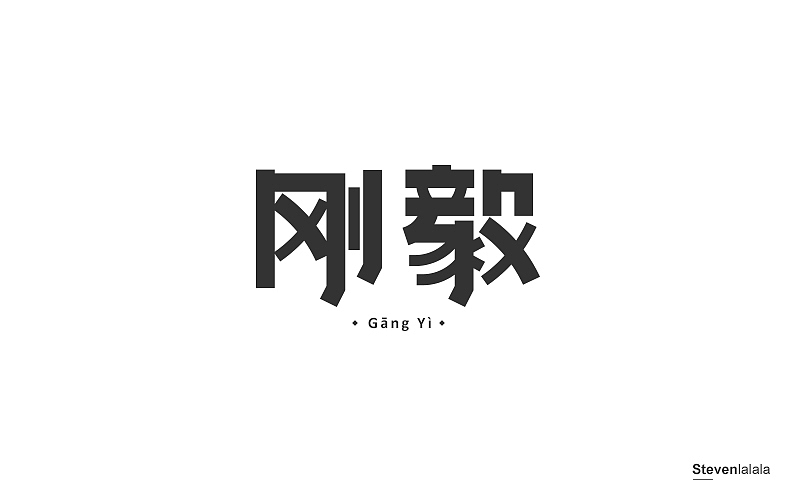
第一次做的题目,当时就想到“困”那个QQ表情。
将笔划拆散之后,出现了马赛克的感觉。
学习了一下使用空白笔划。
做的时候想着“光环”。
自然形成的表情。
甲方爸爸。
懂“艺术”的甲方爸爸。
用水彩叠加了一下。
一般做法,没什么灵感啊。
想到一阵风吹过,有点唏嘘?有点空虚?
黄色丝带。
生日那天做的作品,选为最佳了,开心。
学习一下“虚实”的做法。
比较常规的做法。
也是比较常规的做法。